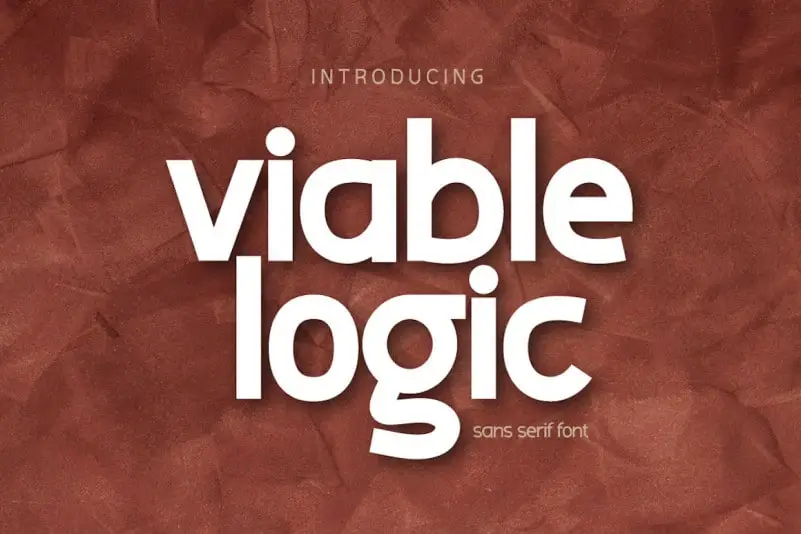
A Viable Logic Sans Serif é uma nova opção para seus projetos digitais buscando algo inovador e moderno. Esta fonte sans serif oferece três versões diferentes: bold, thin e regular. Construída para atender à crescente necessidade de design original e contemporâneo, esta família de fontes não serifa apresenta um equilíbrio entre simplicidade e elegância. Seu design confere-lhe uma aparência clara e moderna, dando também um toque único que lhe proporciona a capacidade de criar uma impressão intrigante em seus trabalhos. Engajantes como ela é, esta fonte será definitivamente uma escolha inteligente para qualquer projeto que busca destacar-se no ambiente digital atual.